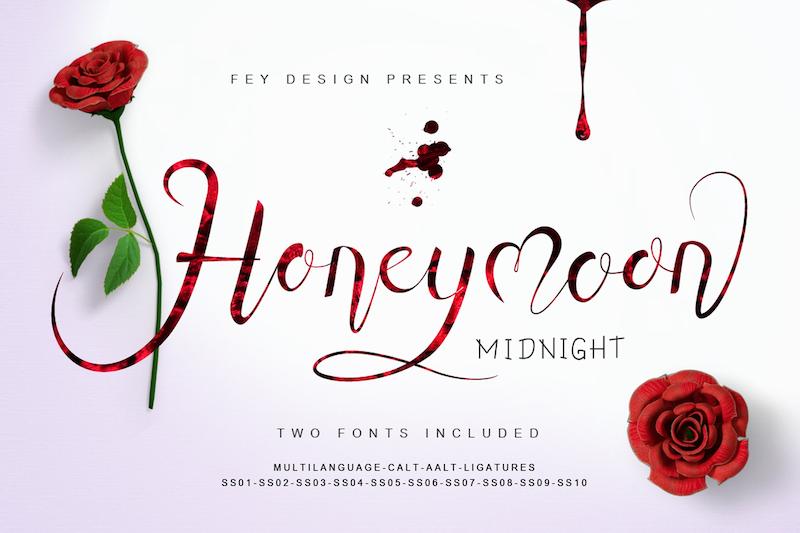
هانیمون میدنایت - دو فونت مناسب برای طراحی المان، عروسی، رویداد، تیشرت، لوگو، نشان، استیکر و کارهای عالی دیگه...
این بسته شامل دو نوع فونت اصلی (کالیگرافی و اسلب) به همراه سواشها (خطوط تزئینی) است.
شامل لیگچرهای استاندارد و آلترنیت برای ایجاد جلوههای خاص است.
از کاراکترهای چندزبانه پشتیبانی میکند.
دارای سبک کالیگرافی مدرن و منحصربهفرد است.
طبقهبندی: اسکریپت و دستنویس